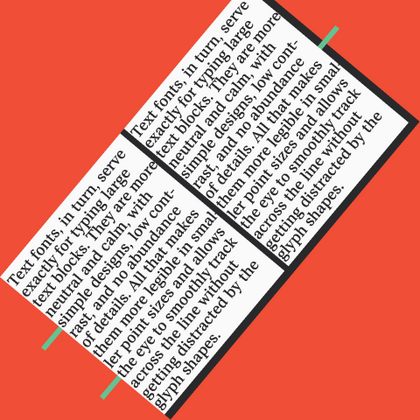
Книжные шрифты
Для издательского дела особенно важны книжные шрифты, где каждая деталь продумана для снижения зрительной нагрузки. Их дизайн сочетает нейтральную красоту с высокой читаемостью: гармоничные пропорции букв, оптимальный межстрочный интервал и узнаваемый характер. В нашем каталоге вы найдёте проверенные временем гарнитуры и новые перспективные разработки — от компактных вариантов для pocket-книг до выразительных шрифтов для детских изданий.
TT Odellia — старостильная антиква с современным рисунком, вдохновлённая венецианскими шрифтами и классической музыкой.
TT Nooks Serif — акцидентная новостильная антиква с лёгким налётом эгоцентричности. У неё острый и твёрдый, при этом элегантный и статный характер.
TT Dott — экспериментальный пиксельный гротеск, в котором за основу пикселя взят круг. Это пластичный и необычный акцидентный шрифт, вызывающий ассоциации одновременно с вышивкой и техно-вечеринками.
TT Supermolot Neue — технологичный модульный гротеск с футуристическим настроением и мощным функционалом. Яркость его характера сочетается с универсальностью применения.
TT Rationalist — функциональный и оригинальный брусковый шрифт с актуальным рисунком. Он универсален и подходит как для заголовков, так и для массивов текста.
TT Commons™ Classic — универсальный геометрический гротеск для широкого круга задач.
TT Bells сочетает в себе элегантную мягкость антиквы с непростым и дерзким характером, который выражается в прямых срезах и клинообразных засечках. В основе шрифта лежит ширококонечное перо, характерное для старостильных шрифтов, создающее эти атмосферные срезы и засечки.
TT Severs — это геометрический гротеск с ярко выраженными элементами внутренних скруглений. Отличительной особенностью TT Severs является необычная форма внутренних овалов, которая отсылает нас к стилю традиционной арабской письменности.
TT Jenevers стилистически относится к голландским антиквам нового стиля. В гарнитуре присутствуют характерные детали, свойственные голландским антиквам — это ассиметричная форма засечек или нерегулярный наклон овалов.
TT Regins — шотландская новостильная антиква с королевским характером. Яркий контраст и острые треугольные засечки придают этому шрифту строгий и властный нрав.
TT Quaris — изысканная и современная ленточная антиква. Перед разработкой этой гарнитуры мы провели глубокое исследование архетипов ленточных антикв.
TT Ricordi Allegria — современная ленточная антиква, отличительные особенности которой, гиперболизированная разноширинность в пропорциях, контраст между штрихами, клиновидные окончания штрихов и отсутствие традиционных засечек.
TT Modernoir — акцидентный гротеск с разноширинными пропорциями. Плавные линии и изящные формы ар-нуво в этом шрифте сочетаются с ритмичностью и импровизационной свободой джаза.
TT Moons — узкая и контрастная антиква. Данное шрифтовое семейство очень элегантно работает в классических темах дизайна. TT Moons по стилистике относится к глиптальным новостильным шрифтам. Идеальная сфера использования TT Moons — это верстка журналов, книг и газет.
TT Ricordi Greto — неконтрастный флорентийский гротеск с динамичными пропорциями. Это единственный гротеск среди антикв в коллекции TT Ricordi, при этом в нем сохранились едва заметные засечки, отсылающие к прототипу.
TT Firs Neue — скандинавский гротеск, сочетающий выразительные графические элементы с универсальностью использования. Мы проанализировали каждый контур и графический элемент. Пересобрали шрифт заново, чтобы сохранить лучшее и исправить необходимое.
TT Fellows — гуманистический гротеск с механистическими мотивами. Открытые формы, дружелюбно-нейтральный характер тонких весов и ещё более мягкий характер в жирных начертаниях.